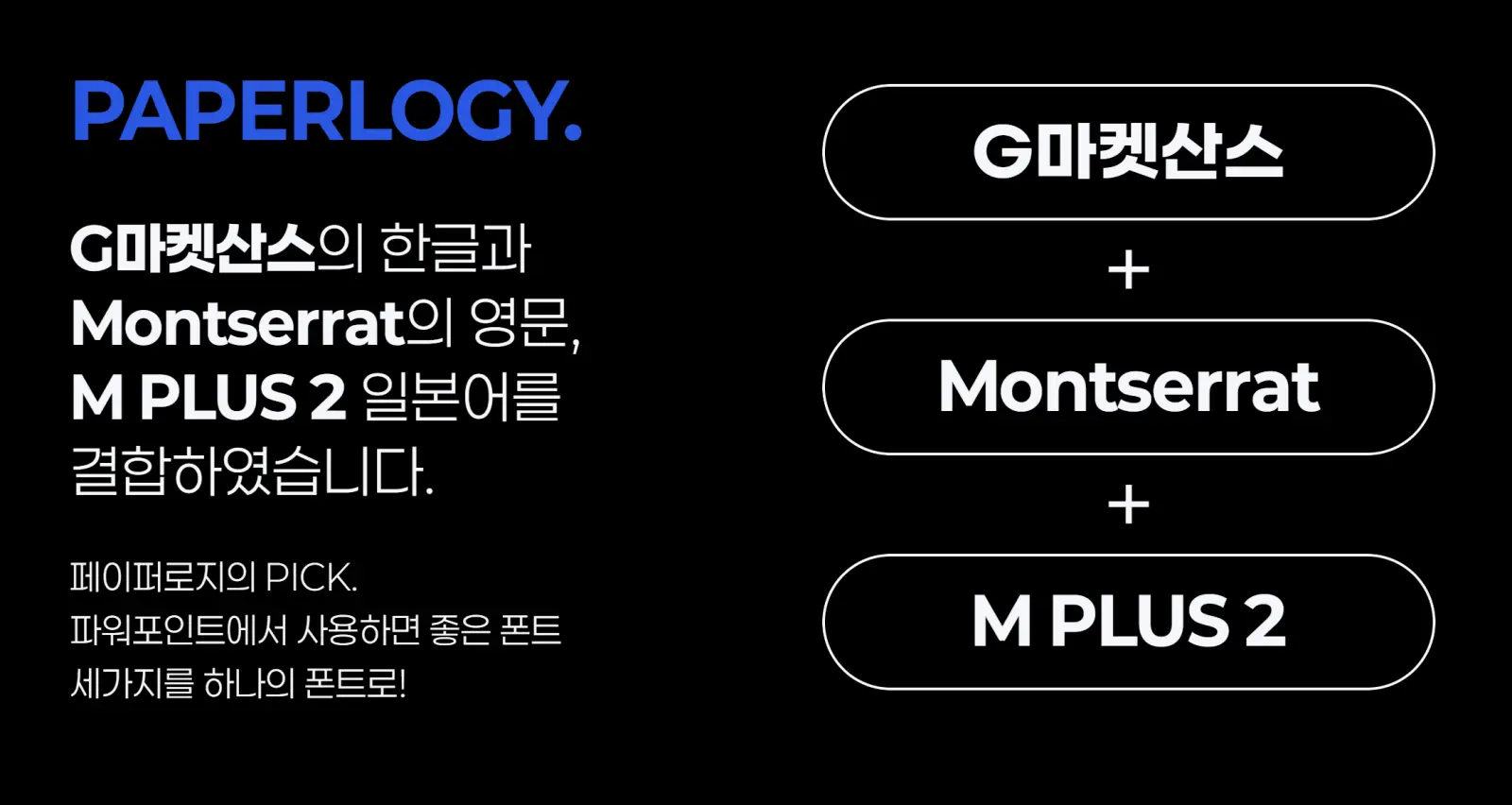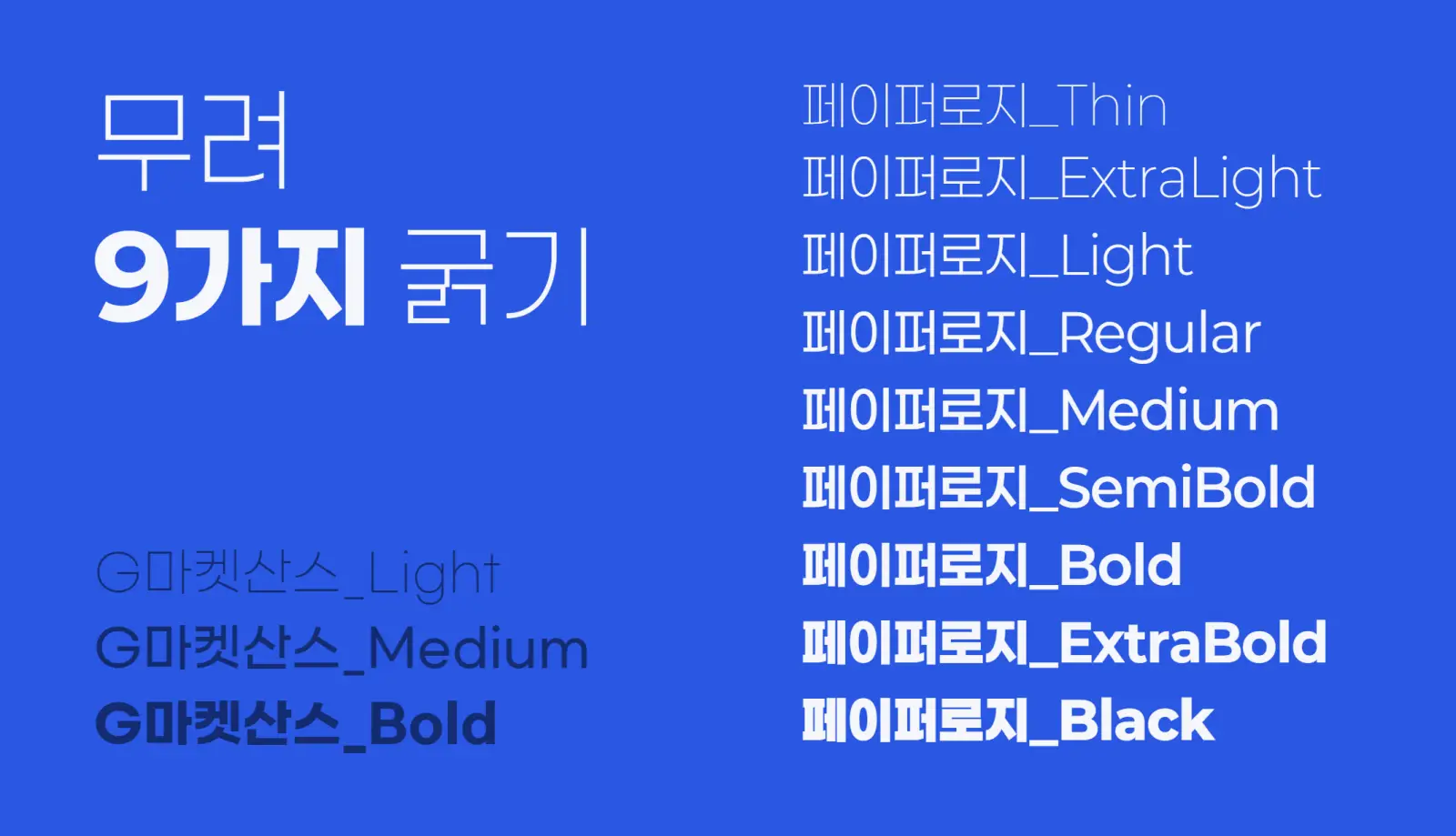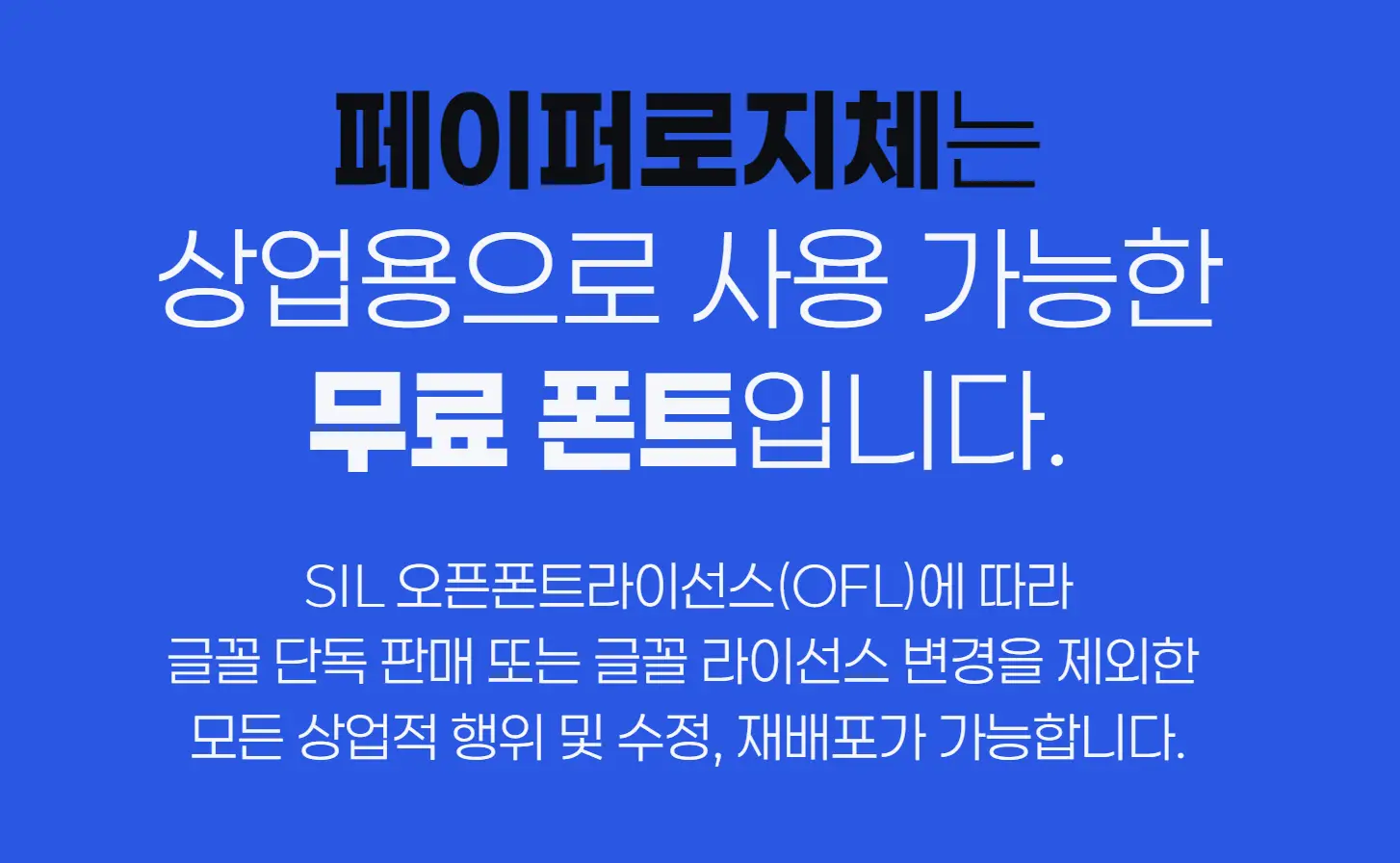
프레젠테이션 작업에서 가장 중요한 요소 중 하나는 가독성과 디자인을 모두 충족시키는 글꼴입니다.
하지만 적합한 폰트를 찾는 일은 쉽지 않습니다.
오늘은 PPT, 보고서, 광고 및 디자인 작업에서 유용하게 활용할 수 있는 페이퍼로지(Paperlogy) 폰트를 소개하고 다운로드 방법을 안내해드리겠습니다.
페이퍼로지는 G마켓 산스체와 Montserrat 영문체를 기반으로 개발된 폰트로, 심미성과 실용성을 동시에 갖춘 것이 특징입니다.
페이퍼로지 폰트의 주요 특징
세련된 디자인과 뛰어난 가독성
페이퍼로지 폰트는 종이를 접은 듯한 독특한 텍스처와 깔끔한 라인으로 만들어졌습니다.
이러한 디자인 요소는 PPT, 광고, 브랜딩 등 다양한 디자인 프로젝트에 적합하며, 텍스트가 주는 메시지를 더욱 효과적으로 전달합니다.
9가지 굵기의 다양한 옵션
페이퍼로지는 Thin, ExtraLight, Light, Regular, Medium, SemiBold, Bold, ExtraBold, Black의 9가지 굵기를 지원합니다.
이로 인해 텍스트의 강조 정도를 세부적으로 조정할 수 있어, 디자인의 완성도를 높이는 데 큰 도움을 줍니다.
고정폭 숫자와 간편한 조정
페이퍼로지는 고정폭 숫자를 제공하여, 숫자의 너비가 일정하게 유지됩니다.
이를 통해 숫자를 자주 사용하는 보고서나 데이터 시각화 작업에서 더욱 정렬감 있는 디자인이 가능합니다.
또한 글자 간격이 기존 폰트 대비 좁게 설정되어 별도의 자간 조정 없이 사용할 수 있습니다.
페이퍼로지 폰트의 활용 팁
- PPT 발표 자료 제작
세미나나 회의 자료 제작 시, 페이퍼로지 폰트를 사용하면 세련된 디자인과 가독성을 동시에 확보할 수 있습니다. - 데이터 시각화
고정폭 숫자를 활용하여 표나 그래프를 정렬감 있게 디자인할 수 있습니다. - 브랜딩 및 로고 디자인
독창적인 텍스처와 가독성 덕분에 브랜드 로고나 슬로건 제작에 적합합니다. - 온라인 콘텐츠 제작
페이퍼로지 폰트는 블로그, 유튜브 썸네일, 인스타그램 포스트 등 다양한 디지털 콘텐츠에도 활용할 수 있습니다.
한글과 영문을 기본으로 지원하며, 일본어 포함 버전도 선택 가능합니다.